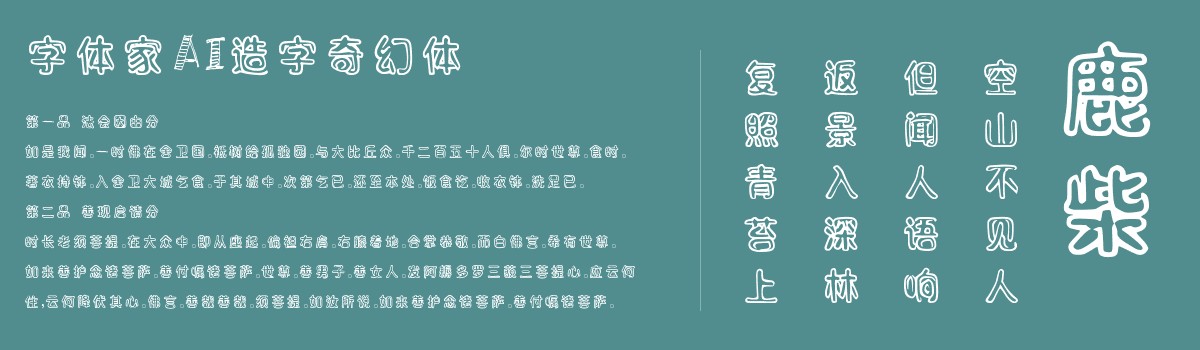
字体家AI造字奇幻体
字体家AI造字奇幻体是一款由字体家AI神笔造字生成的一款艺术字体。笔画以黑体为基底,空心设计。笔画两侧有波浪状曲线装饰,折角处呈圆弧过渡而非直角。部分笔画中段融入星形或月牙形镂空设计,线条粗细均匀却在转折处微微加粗,似有光晕包裹。整体结构饱满偏圆润,重心略高,给人轻盈灵动又带神秘奇幻的感觉,仿佛笔画由星光编织而成。比较适合用于艺术类装饰文字,海报、网页、广告设计,室内装饰,平面标题设计、食品包装、品牌标志等。